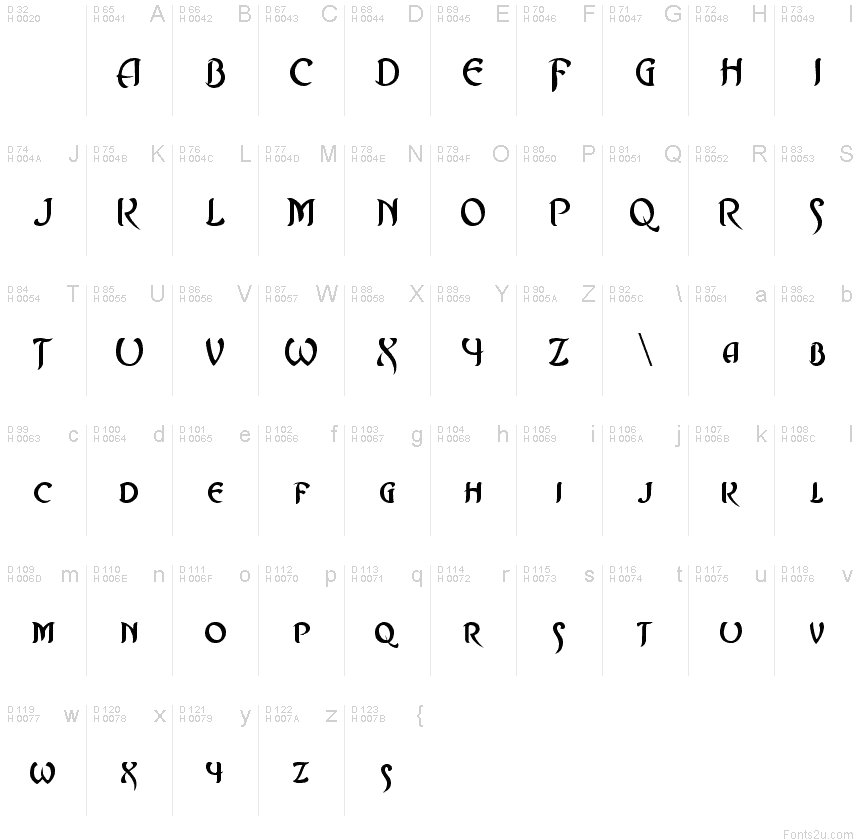
Krój pisma Asrafel od Davida F. Nalle – Scriptorium Fonts to darmowa czcionka ozdobna w stylu retro z mrocznym, baśniowym charakterem. Jej wysokie, zwężające się linie wyglądają, jakby zostały wycięte nożem kaligrafa – pełne ostrych haczyków i zamaszystych krzywizn, które wyginają się nieco bardziej, niż można by oczekiwać. Litery łączą się w gęstą, nasyconą teksturę, która jest jednocześnie teatralna i lekko złowieszcza, przypominając napisy z zapomnianego filmu fantasy lub starej książki o okultyzmie.
Dzięki Asrafel Twoje nagłówki od razu zyskują mityczną, nieziemską obecność, która przykuwa uwagę już z daleka. Ten darmowy font świetnie sprawdzi się na okładkach książek, w grach fantasy, logotypach zespołów, plakatach w stylu gotyckim, tematycznych menu restauracyjnych oraz tytułach wydarzeń, gdzie nastrój jest ważniejszy niż ścisła czytelność. Stosuj go w dużym rozmiarze, daj mu przestrzeń do oddychania i zestaw z prostym krojem bezszeryfowym w tekstach uzupełniających, aby pozwolić jego kunsztownym krzywiznom opowiedzieć historię.